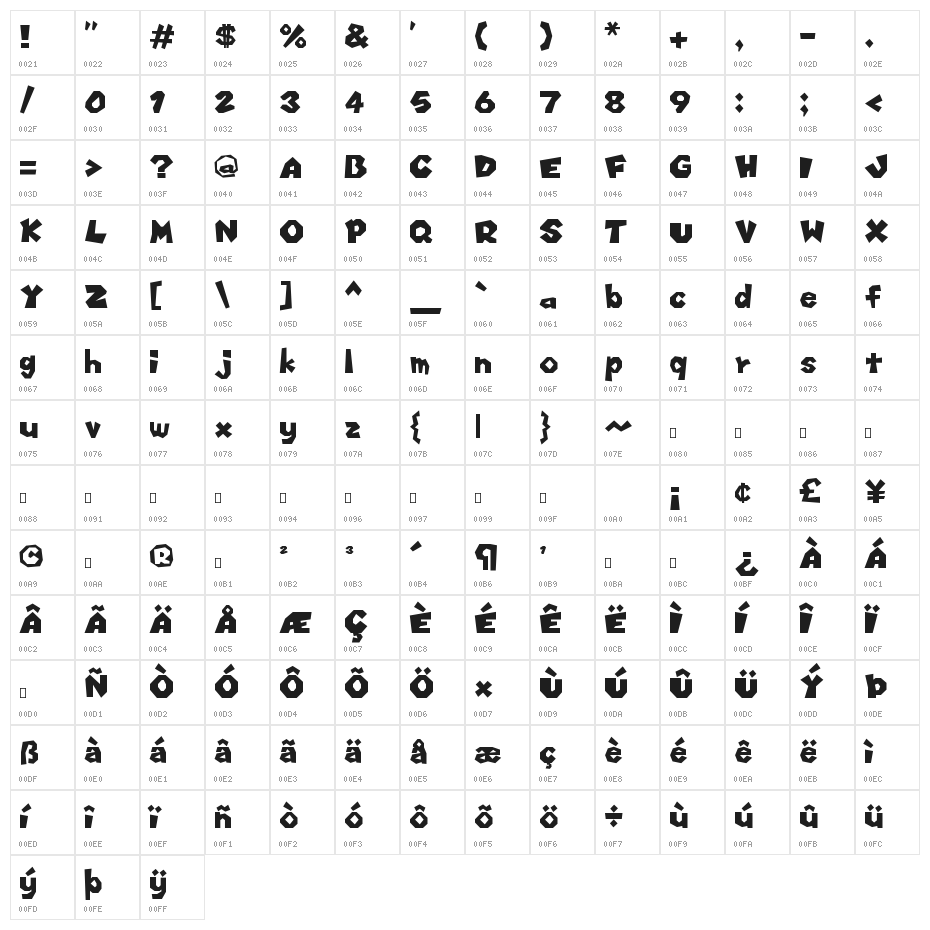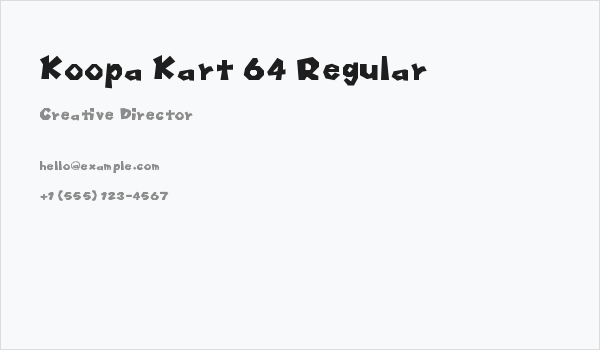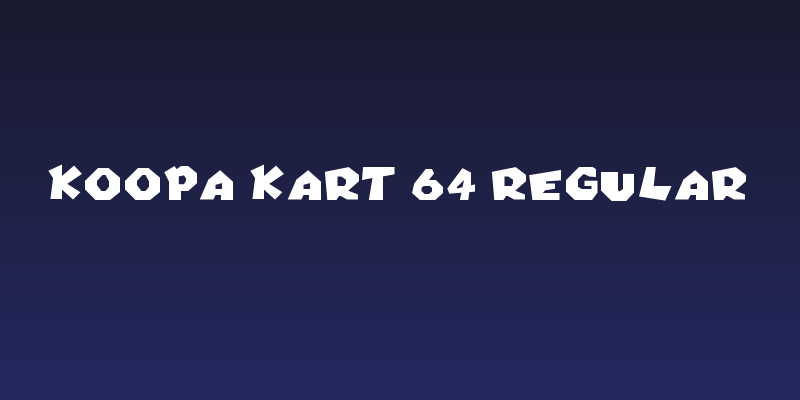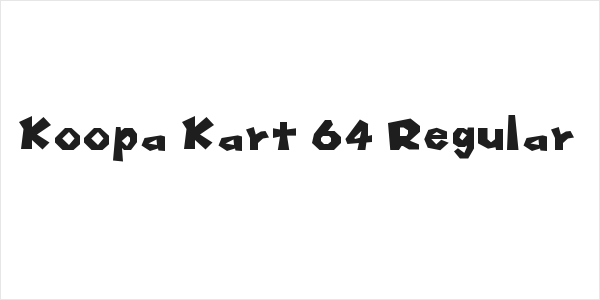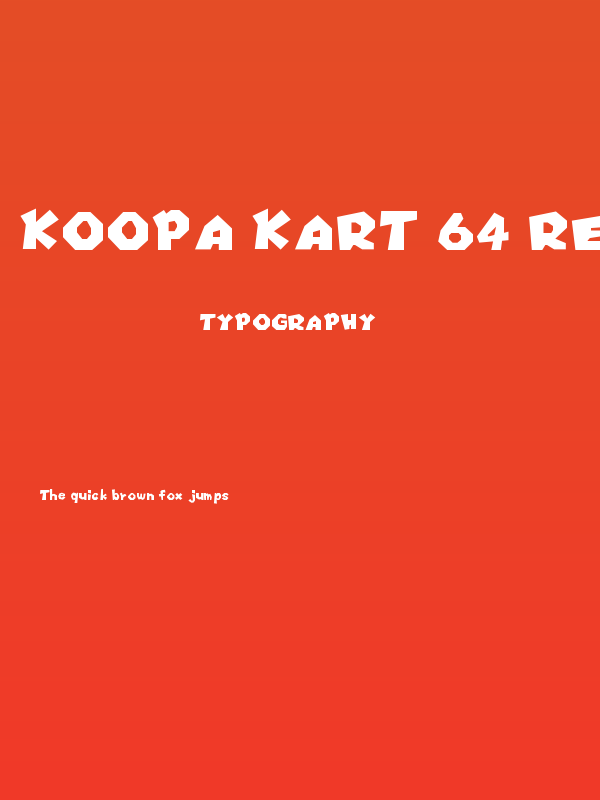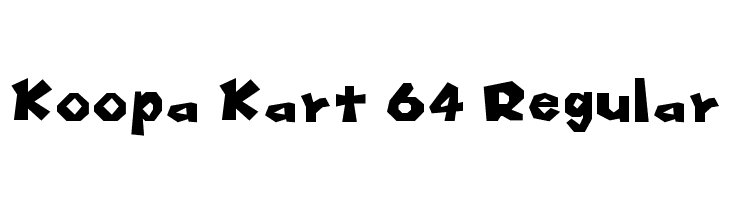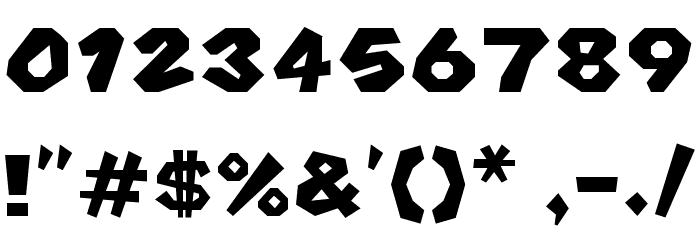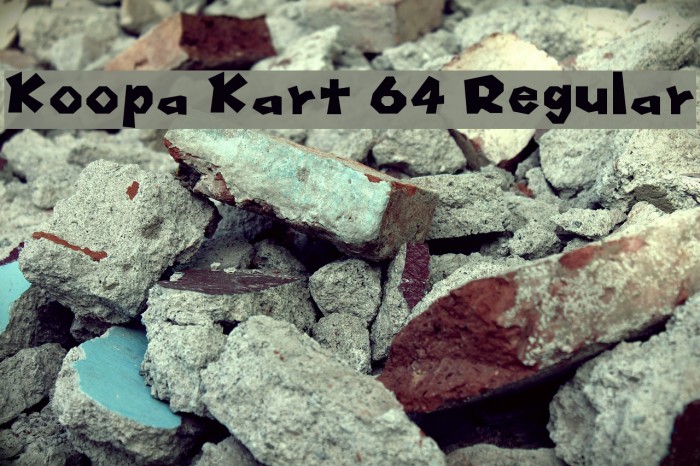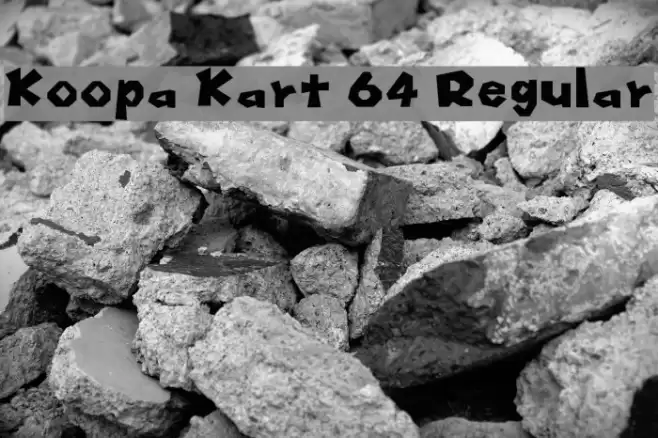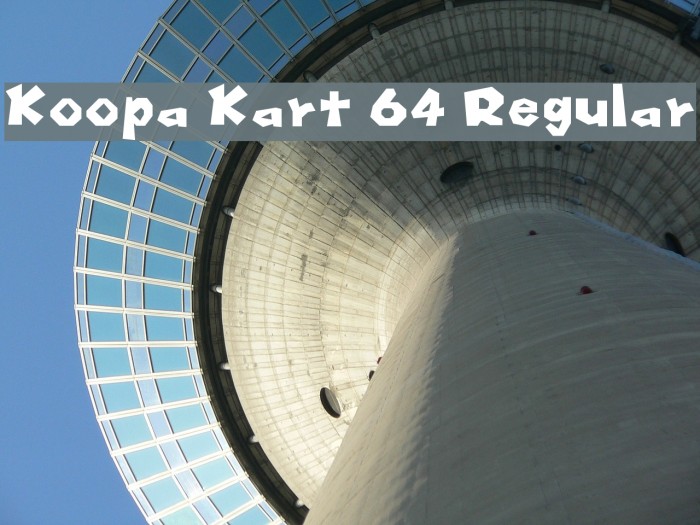
Koopa Kart 64 Regular Font
| Style général | Playful, Energetic, Quirky |
| Projets proposés | Great for video game titles, children's books, posters, and any project needing a fun, energetic typeface. |